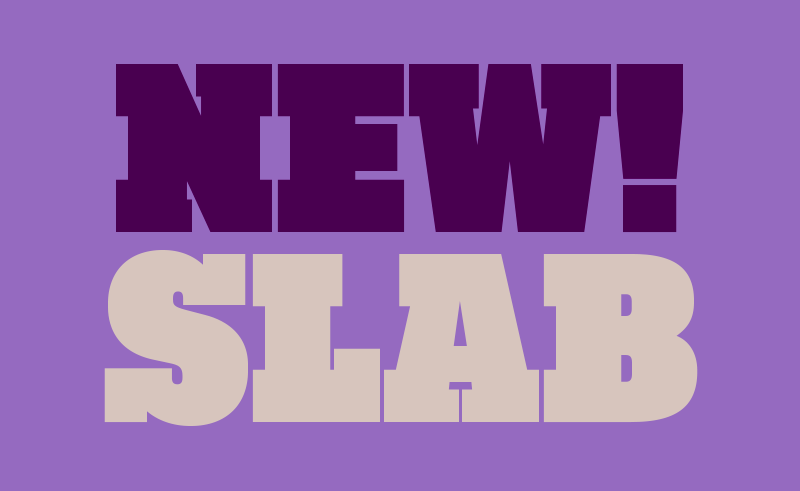
Descubra uma nova opção para suas criações visuais com Akkordeon Slab Font Family, uma seleção de 14 tipos em família de caracteres slab serif criada pela Emtype Foundry. Esta é uma excelente adição ao seu arsenal criativo, oferecendo mais opções e maior liberdade para personalizar design por projetos específicos. Akkordeon Slab traz à tona o espírito original do Akkordeon, mantendo a estrutura de fonte semelhante, mas adaptando as ideias e conceitos em uma nova forma. Isso resulta num forte tom que enriquece toda a família de caracteres, tornando-o especialmente adequado para aplicações como esportes, negócios, moda ou qualquer situação exigindo headlines impactantes. Em um mundo cheio de opções, Akkordeon Slab é uma escolha sólida e vibrante que certamente adicionará um novo nível de destaque à sua próxima criação visual.